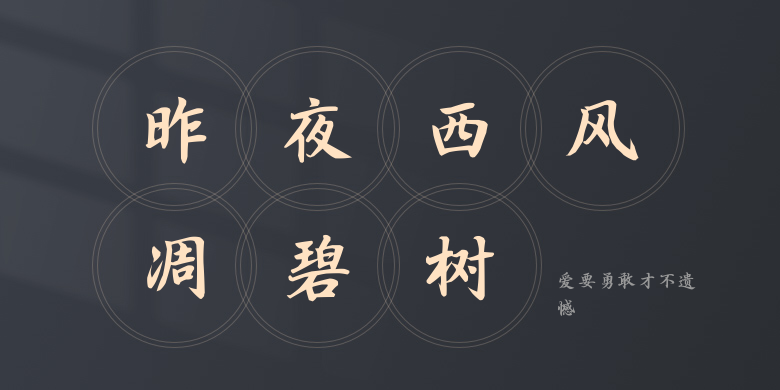
爱要勇敢才不遗憾
爱要勇敢才不遗憾,这款字体结构工整、笔画清晰,兼顾美观与易读性,适用于标题、正文、海报、包装、LOGO 等多种场景。字形优雅稳定,风格百搭耐看,适配日常排版与创意设计,让文字呈现更舒适、更具质感。爱要勇敢才不遗憾一笔一画,皆是细节,以均衡的比例、流畅的线条打造舒适视觉体验,字形端正大气,风格简约现代。无论是商业设计、品牌宣传还是日常排版,都能轻松驾驭,让文字更有格调与力量。爱要勇敢才不遗憾字体下载。